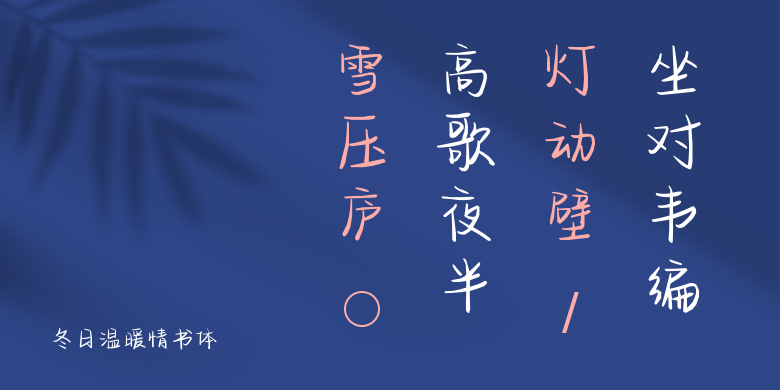
冬日温暖情书体
冬日温暖情书体,这款字体结构工整、笔画清晰,兼顾美观与易读性,适用于标题、正文、海报、包装、LOGO 等多种场景。字形优雅稳定,风格百搭耐看,适配日常排版与创意设计,让文字呈现更舒适、更具质感。冬日温暖情书体一笔一画,皆是细节,以均衡的比例、流畅的线条打造舒适视觉体验,字形端正大气,风格简约现代。无论是商业设计、品牌宣传还是日常排版,都能轻松驾驭,让文字更有格调与力量。冬日温暖情书体字体下载。